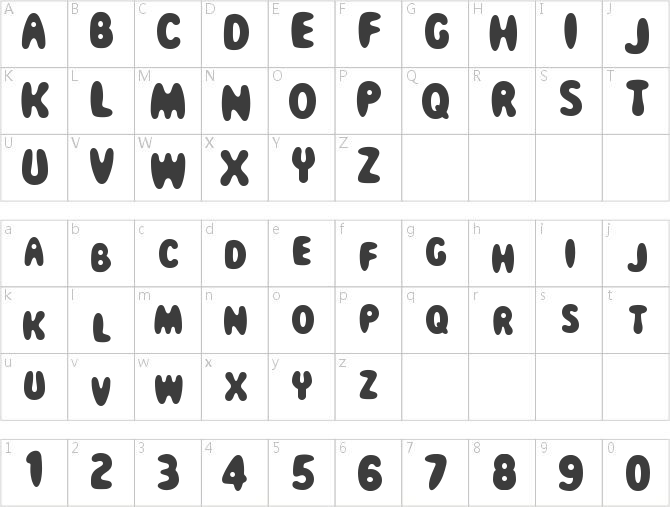
MagicalMysteryTour 詳情頁
字體名稱: Magical
MagicalMysteryTour
MagicalMysteryTour字體字庫是一款讓人賞心悅目、百看不厭的英文字體,適合各類廣告和產(chǎn)品包裝設計應用,字體大小0.09MB,格式為ttf字體,上傳用戶是xqy,作者/版權方為未知